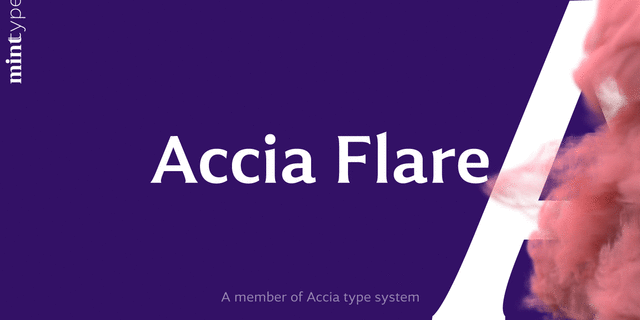
Accia Flare – элегантный глиптальный шрифт с большой высотой строчных и низким контрастом. Его тонкие изгибы создадут нежный, но заметный образ в дизайне упаковки. Шрифтовое семейство содержит 8 начертаний от Thin до Extra Bold с соответствующими курсивами. Каждое начертание имеет обширную языковую поддержку, включая кириллицу, а также многочисленные функции OpenType: капитель, лигатуры, несколько наборов цифр, пунктуация с учетом регистра, дроби и индексы. Accia Flare является частью супергарнитуры Accia, куда входят пять шрифтов, от гротеска до выразительной антиквы. Это дает вам возможность проектировать максимально сложные серии продукции или информационные системы. Система Accia состоит из Accia Sans, Accia Flare, Accia Piano, Accia Moderato и Accia Forte. Гарнитуру разработал Андрей Константинов в студии Mint Type в 2021 году.
тонкий, худой, утонченный, холодный, деликатный, чистый, легкий, свежий, модный, качественный, культурный, отборный, благородный, гармоничный, элитный, дорогой, роскошный, красивый, мастерский, знаменитый, оригинальный, богатый, городской, прозрачный, острый, элегантный, ювелирный, эстетичный, изящный, художественный, драгоценный, гламурный, динамичный, комильфо, сексуальный, вежливый, эффектный, выразительный, характерный, прекрасный, аристократичный, исторический, королевский, пафосный, традиционный, уникальный, имперский, яркий, артистичный, каменный, праздничный, сильный, героический, легендарный, мотивирующий, заметный, броский, фундаментальный, торжественный, эпический, амбициозный, авторитетный, римский, властный, зрелищный, грандиозный, великий, величественный, монументальный, устойчивый, уверенный, архитектурный, кинематографичный, христианский, убедительный, вкусный, аппетитный